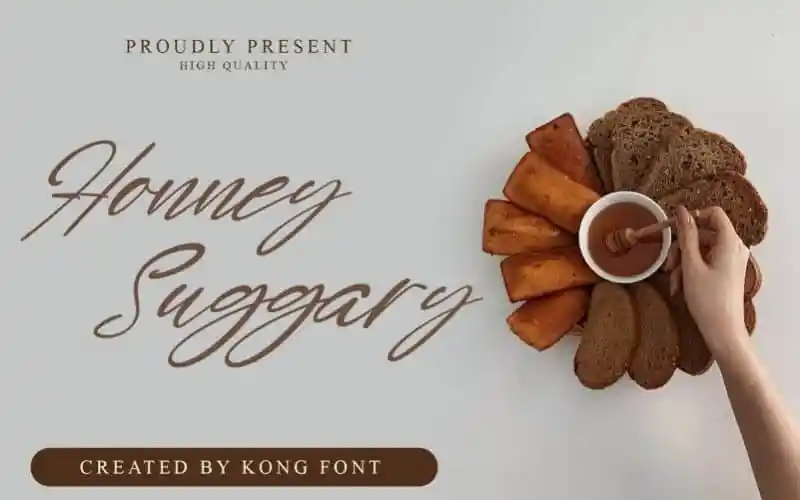
Honney Suggary Script Font
Honney Suggary Script Font é uma fonte elegante e sofisticada que traz modernidade ao seu design junto com uma pitada de clássico, criando um resultado único. Este texto é perfeito para criar um visual atraente em suas plataformas sociais, anúncios do Pinterest, convites impressos ou qualquer outra peça de identificação visual que você possa estar produzindo. Além disso, sua elegância transmite confiabilidade e sofisticação, tornando-a uma escolha perfeita para personalizar seu website e outras mídias digitais. Quebre a monotonia dos textos com Honney Suggary Script Font e invista em um design que destaca sua marca ou evento.